「サスペンス」にピッタリのおすすめフリーフォント
今回は、ハラハラドキドキする展開が面白い「サスペンス」の雰囲気にぴったりなフリーフォントをご紹介します。
「サスペンス」といえば、推理ドラマ、探偵ストーリー、小説などの作品で、不安感や緊張感などを伴う心理的恐怖を表現したジャンルです。今回は、そんなサスペンスの世界観にぴったりなフォントを紹介します。ぜひ参考にしてみてください。
サスペンスにおすすめのフォントまとめ
サスペンスジャンルのバナーデザイン・動画制作・広告制作・サムネイルで幅広く使えるフォントです。
瀞ノグリッチ
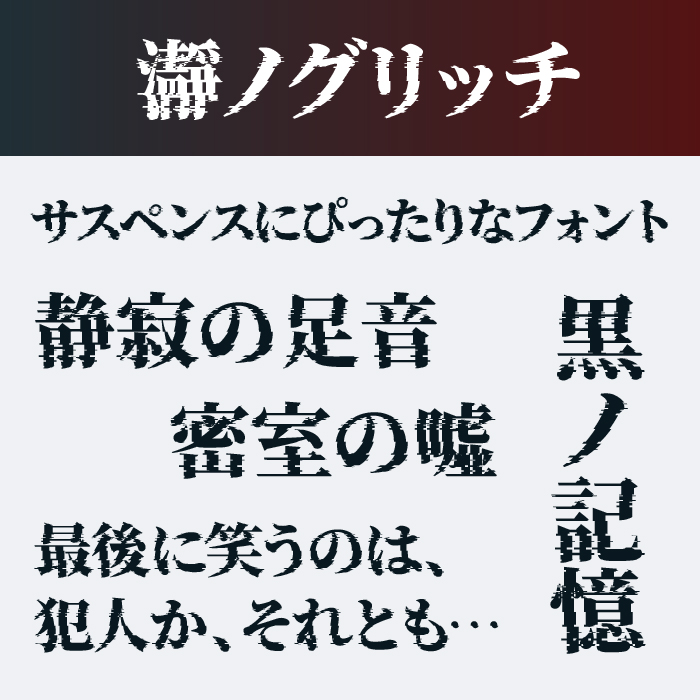
瀞ノグリッチ明朝フォントは、源ノ明朝をベースにグリッチエフェクトの処理を施したかっこいい明朝体のフォントになっています。
ノイズ感がサスペンスな雰囲気にぴったりです。
焚火フォント
焚火フォントは、文字が燃えているようなフォルムをしているので、ミステリー系・サスペンス系・ホラー系などのジャンルで効果的に使えるフォントです。
KazukiReiwa(一樹令和)
KazukiReiwa(一樹令和)フォントは、墨溜まり加工が施されている上品で、柔らかい印象をもつオールドスタイルの明朝体フォントです。3つのウェイトがあり、一番細いウェイトだと、線が消えていきそうな華奢なフォルムが、サスペンスな雰囲気にぴったりハマります。
百鬼夜行
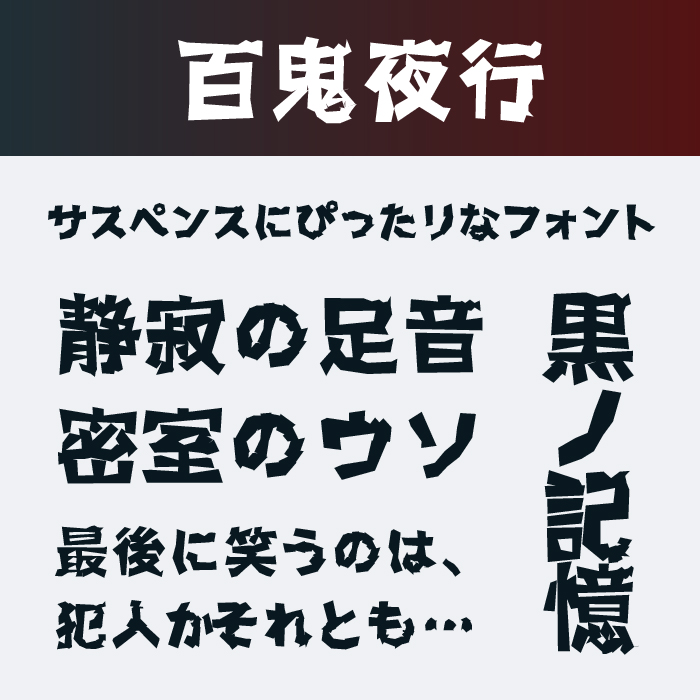
百鬼夜行フォントは、文字の輪郭がジャギジャギとしているデザインで、ホラー感を感じさせるデザインフォントです。可愛らしい雰囲気もあるので、コミカルさのあるサスペンスにおすすめです。
水面字
水面字フォントは、水面に映る、ゆらめく文字をイメージされて制作されたデザインフォントです。文字のゆらぎがダイイングメッセージのような滲みを感じるデザインです。
あおさぎ
あおさぎフォントは、柔らかく可愛らしさも感じる明朝体は、サスペンスのタイトルなどにぴったりなフォントです。
しねきゃぷしょん
しねきゃぷしょんフォントは、映画で使われているの日本語字幕データをもとに作成された、映画の字幕のようなフォントです。
コミック古印体
g_コミック古印体フォントは、古印体風に作られたの手書きフォントです。
ICHIGAYA明朝体
ICHIGAYA明朝体フォントは、秀英舎活版製造所の活字をベースに制作された明朝体フォントです。あえて不揃いな雰囲気がサスペンスの世界観にぴったりです。
ふぉんとうは怖い明朝体
ふぉんとうは怖い明朝体フォントは、文字にグニャーっとゆらぎの加工を施した少し怖い印象があるフォントです。
コミックホラー悪党
g_コミックホラー悪党フォントは、毒々しく、サスペンスやホラーを感じる不安感が煽られているようなデザインとなっています。